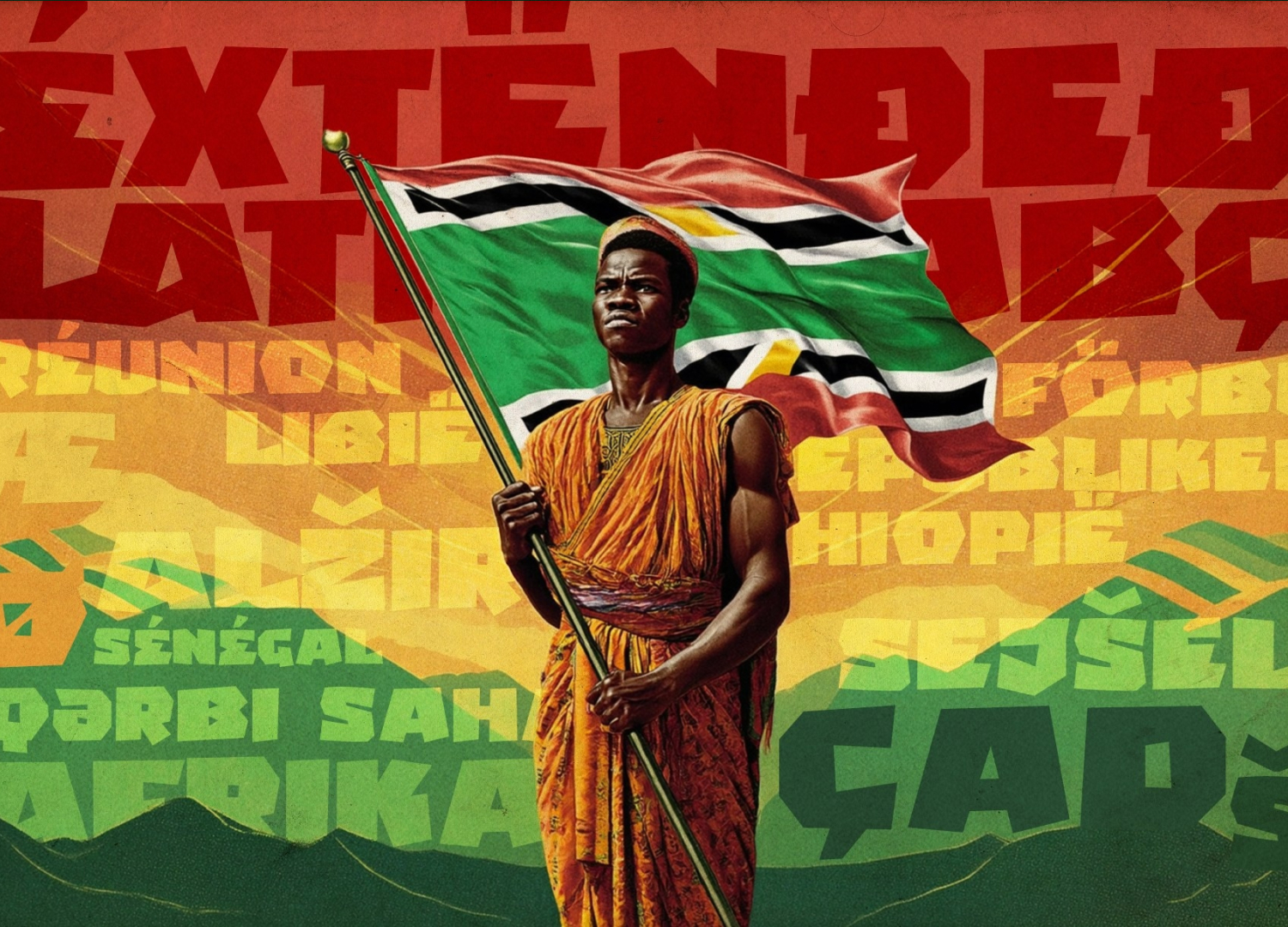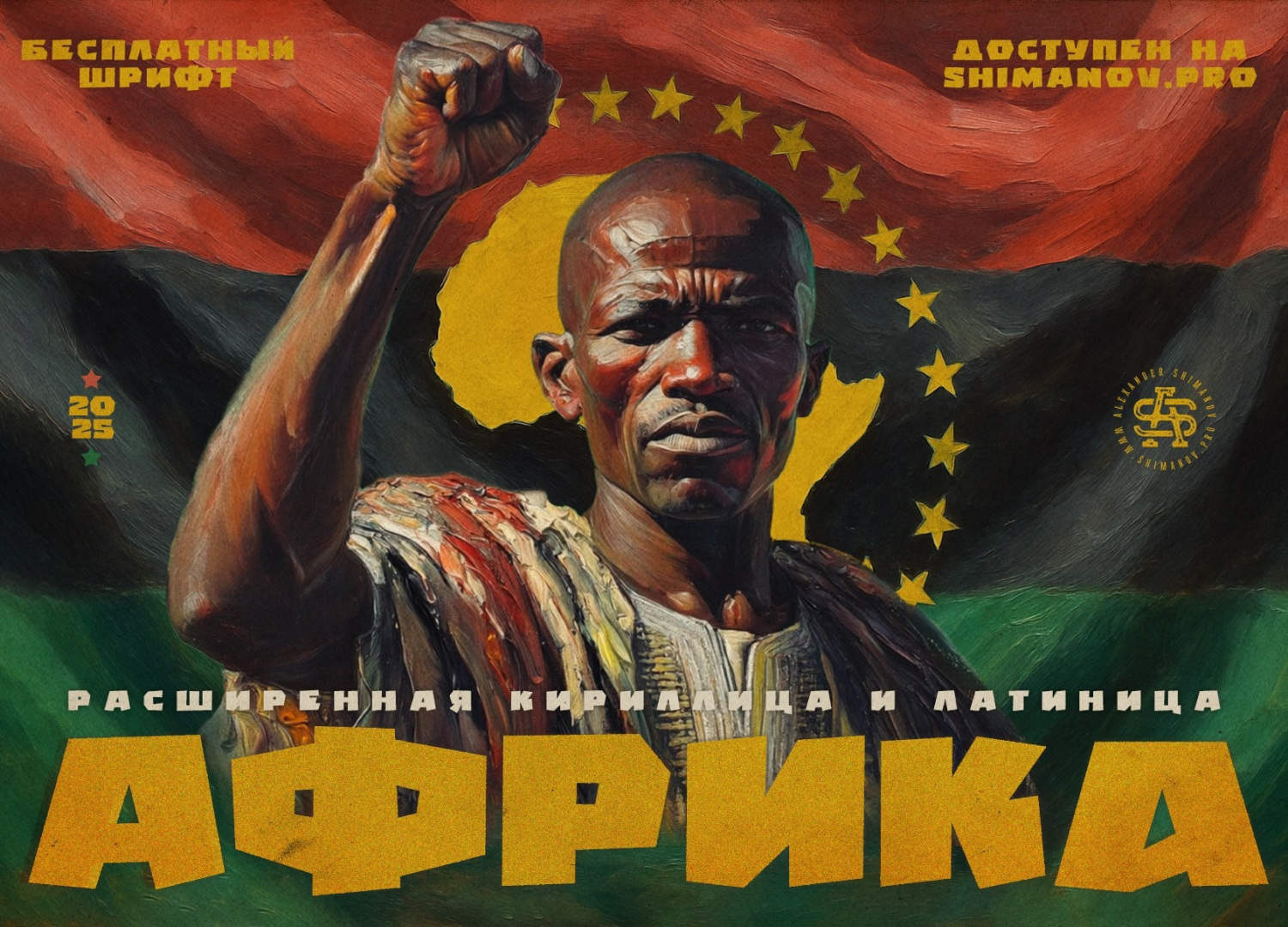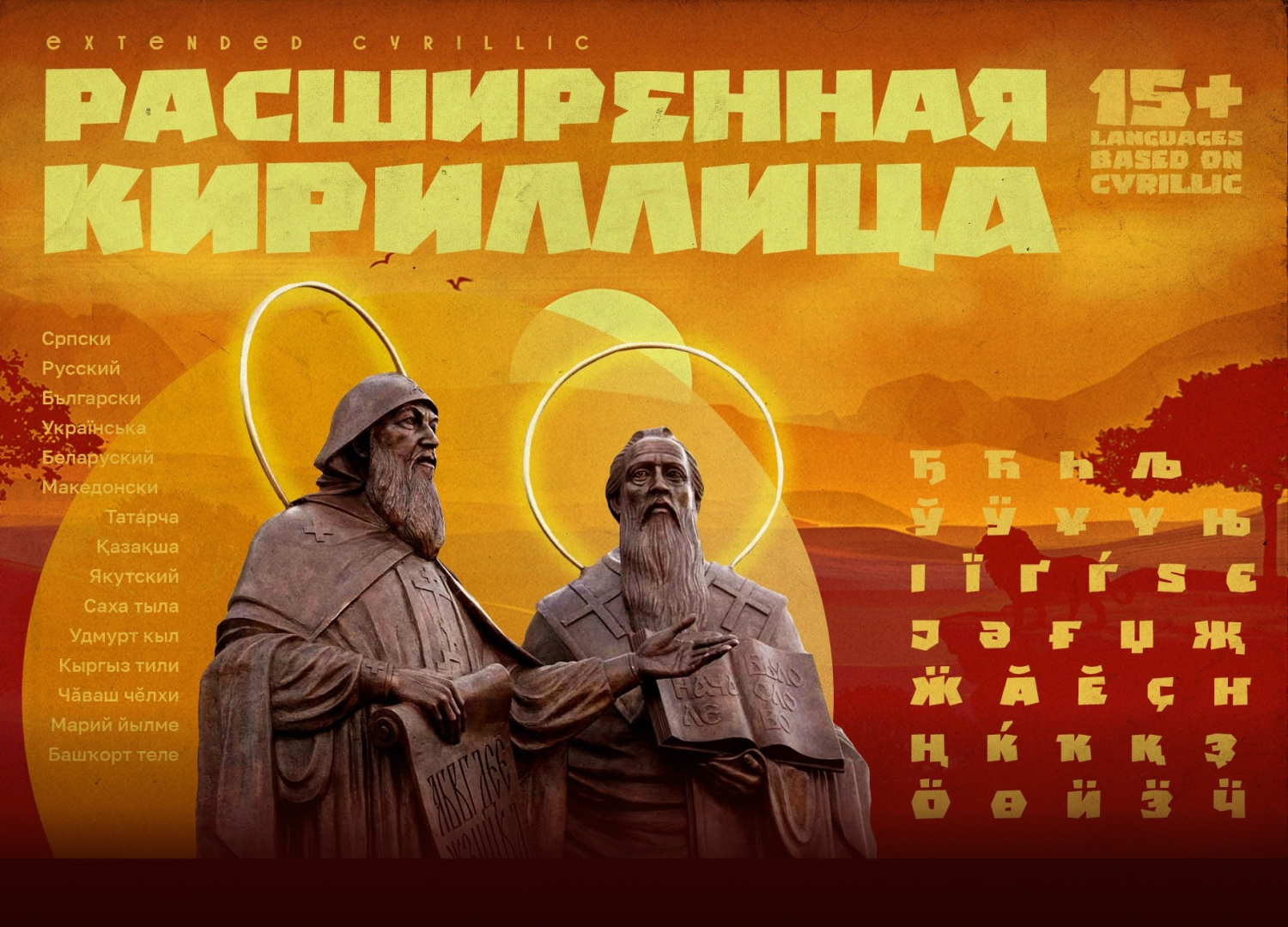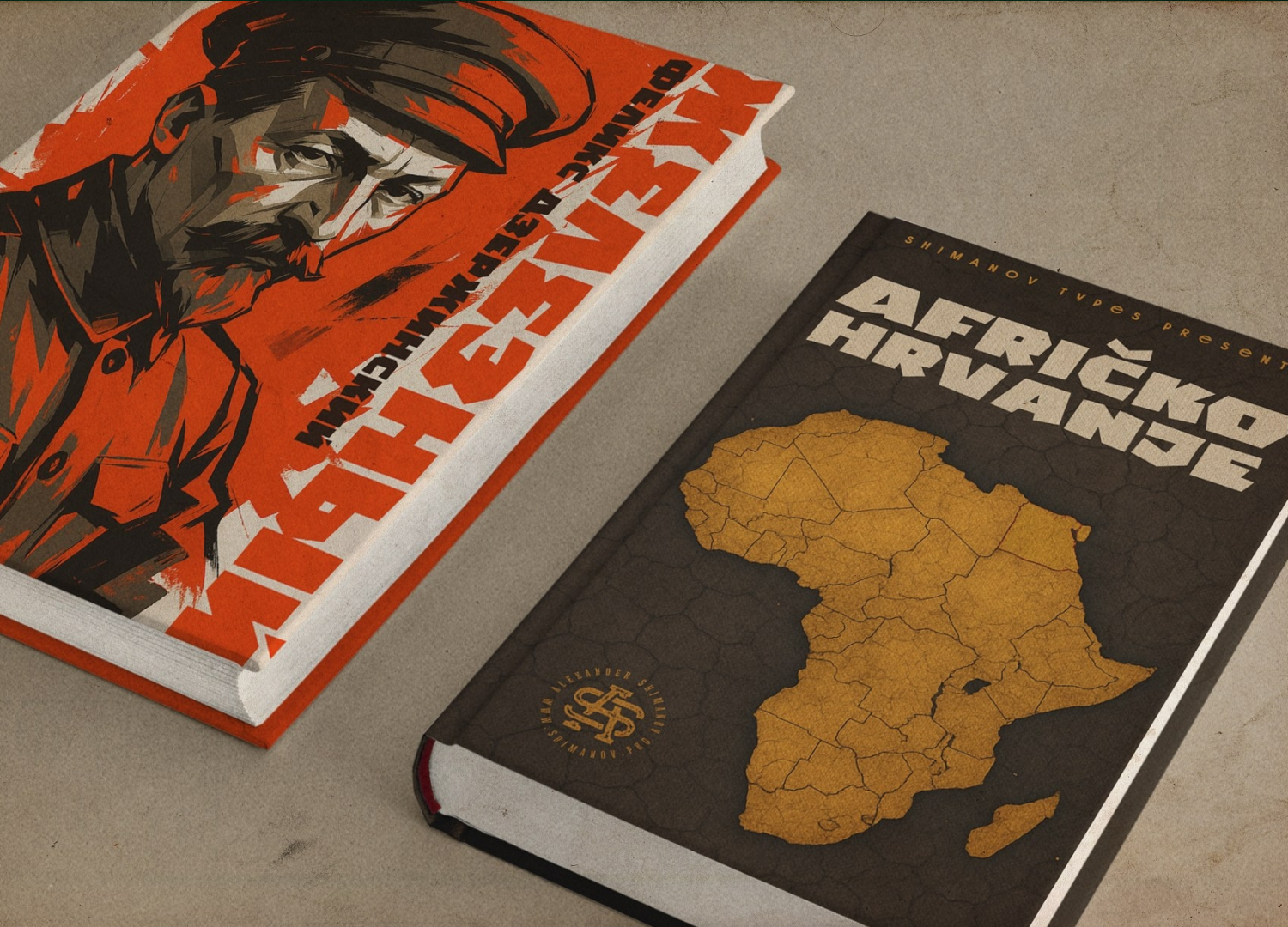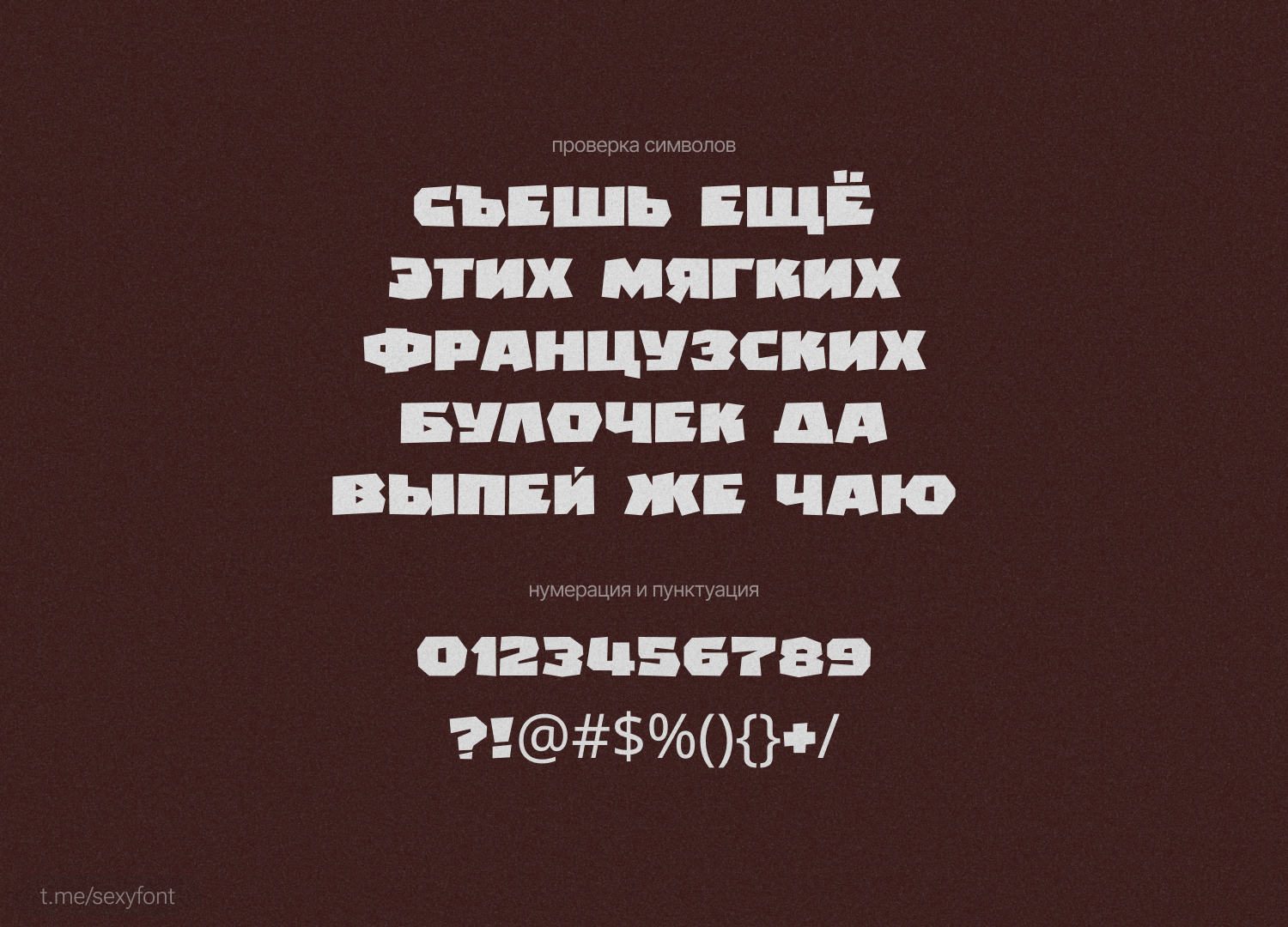
Бесплатный Шрифт ST-Africa
Продолжаю собирать кириллицу. Шрифт ST-Africa. Шрифт наследие советских агитационных плакатов посвящённых борьбе африканских народов с колониализмом.
Ярко выраженная акциденция, крупные, резкие формы.